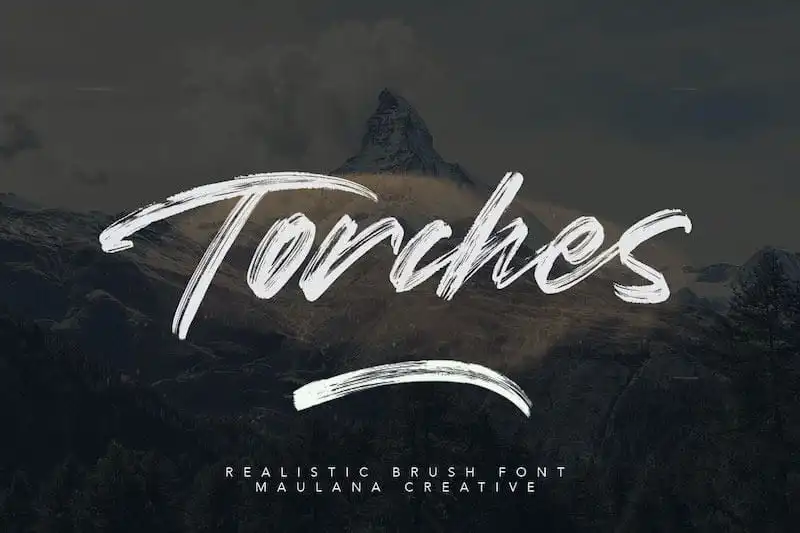
Torches Brush Font – Download Grátis
Introduzimos Torches Brush Font, uma tipografia que captura a elegância do traço natural da mão escrita rápida. Essa fonte foi projetada e compartilhada pelo Maulana Creative. Perfeita para cartões de签名、标志设计、产品包装、宣传材料、时尚杂志和书籍封面等创意项目。Torches Brush Font é perfeitamente adaptável a vários fins, desde cartazes até postagens nas redes sociais. Composta para escrever citações escritas à mão, ela também pode ser usada em materiais de merchandising e logotipos de marca, garantindo um toque autêntico em qualquer aplicação. Uma das suas principais vantagens é a sua versatilidade: você pode usar esta fonte para criar cartões de visita elegantes ou até mesmo uma mensagem de vídeo personalizada. Torches Brush Font torna-se a escolha ideal se estiver procurando por uma solução criativa que combine o mundo da arte com a eficiência no design digital, permitindo ao designer expressar sua identidade visual de maneira única e autêntica.